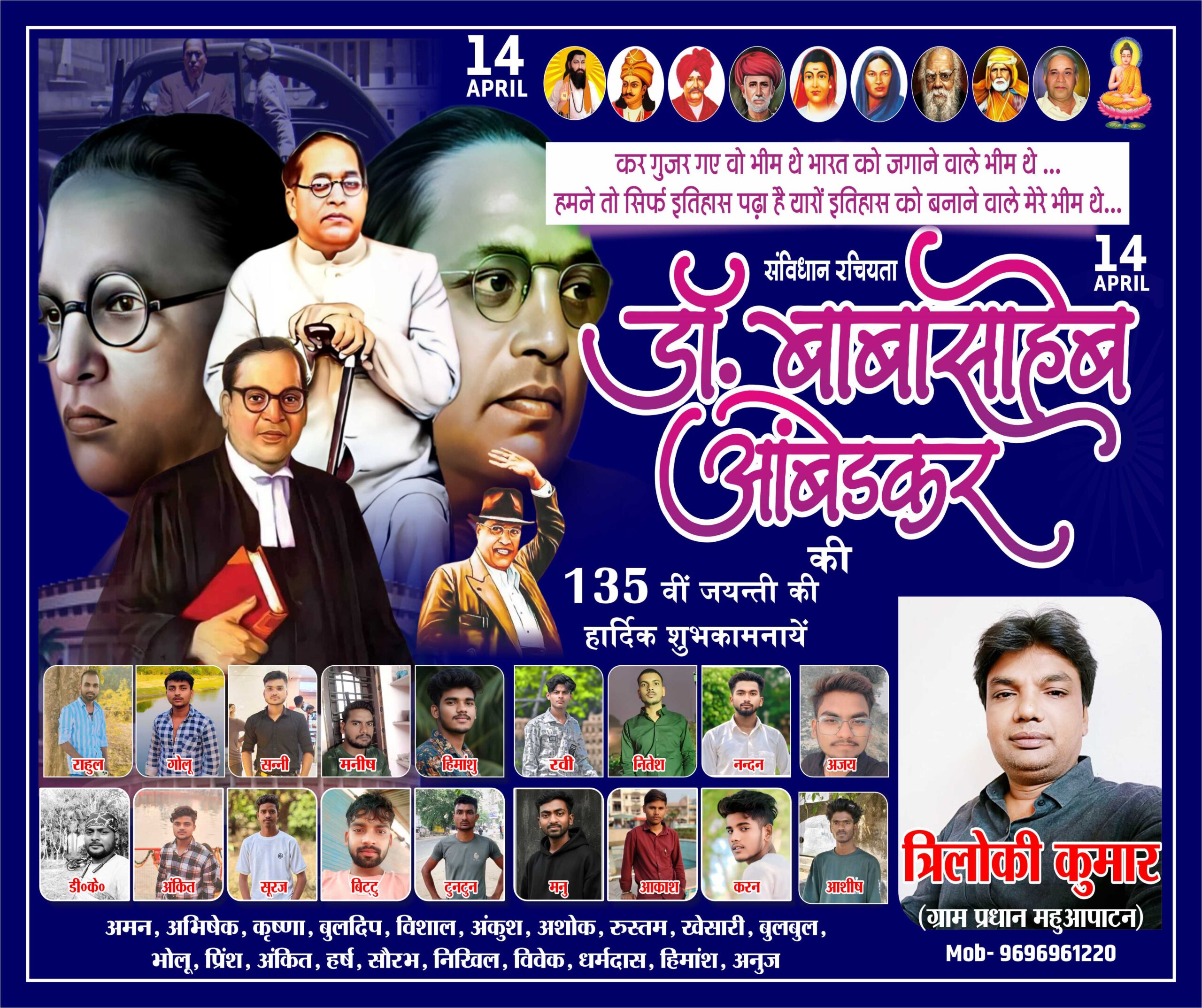
14 April Baba Saheb Jayanti CDR Poster with Font
इस बैनर डिज़ाइन में गहरे नीले रंग (Royal Blue) के बैकग्राउंड का उपयोग किया गया है, जो बाबासाहेब के प्रतीक और आदर्शों को दर्शाता है। इसमें डॉ. अंबेडकर के विभिन्न जीवन काल की एचडी तस्वीरों का एक सुंदर कोलाज बनाया गया है।
डिज़ाइन की विशेषताएं:
प्रभावी टाइपोग्राफी: “डॉ. बाबासाहेब अंबेडकर” नाम को स्टाइलिश कैलीग्राफी हिंदी फोंट में लिखा गया है, जो पोस्टर को एक प्रोफेशनल लुक देता है।
मल्टी-फोटो सेक्शन: इसमें ग्राम प्रधान या आयोजकों के लिए एक बड़ा फोटो फ्रेम और कार्यकर्ताओं के लिए 18 छोटे वर्गाकार फोटो फ्रेम दिए गए हैं, जिन्हें आप आसानी से बदल सकते हैं।
प्रेरक कविता: पोस्टर के मध्य में बाबासाहेब के सम्मान में भावपूर्ण कविता शामिल की गई है, जो दर्शकों को प्रेरित करती है।
मुख्य विशेषताएं (Key Highlights)
सभी महापुरुष शामिल: बैनर के टॉप पर भगवान बुद्ध और अन्य महापुरुषों के चित्र शामिल हैं।